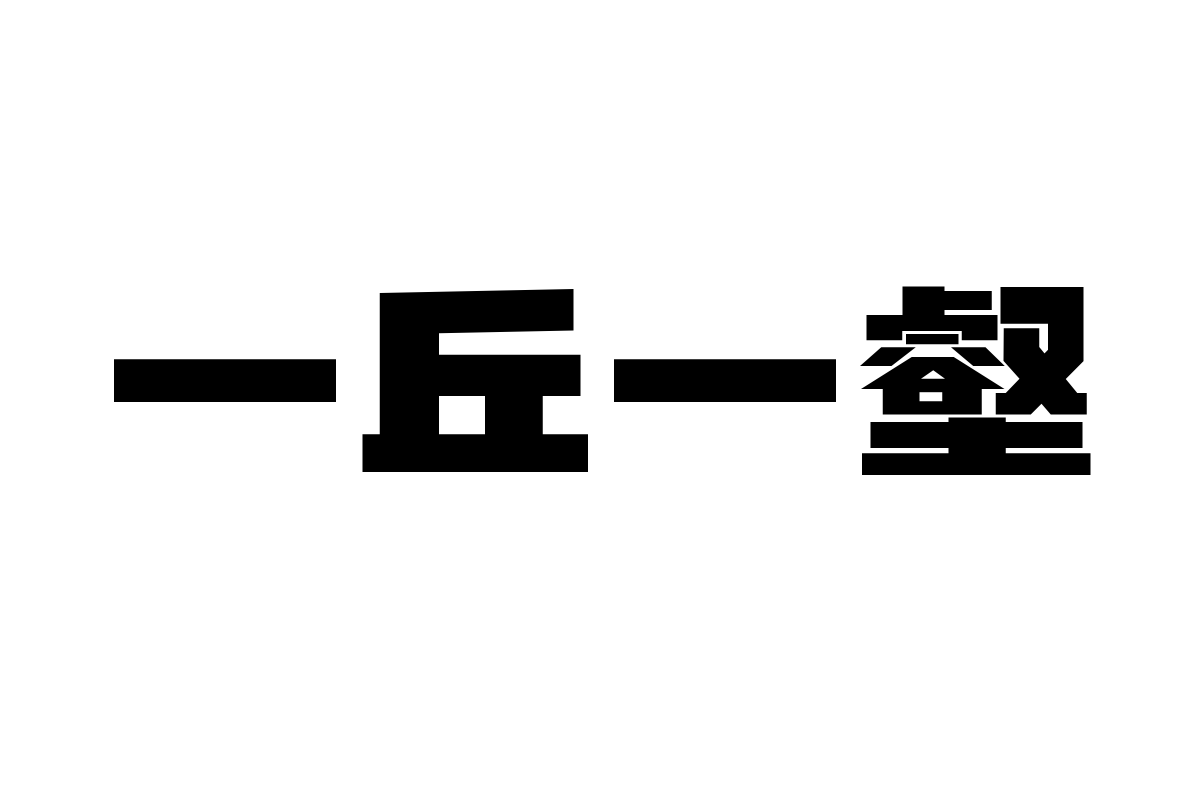
山海潮流超黑字体是一款具有独特风格的中文字体,它采用了现代的设计手法和创新的设计理念,将传统书法与现代审美相结合,打造出了一种独特的视觉体验。这款字体的特点如下:
1. 字形结构:山海潮流超黑字体的字形结构紧凑,线条流畅,给人一种动感十足的感觉。它的笔画粗细不一,既有粗犷豪放的一面,又有细腻柔和的一面,使得整体风格既大气又不失个性。
2. 字形风格:这款字体的字形风格独特,既有传统的韵味,又融入了现代的元素。它的笔画变化多样,既有直线的硬朗,又有曲线的柔美,使得整体风格既有力量感又不失美感。
3. 字间距:山海潮流超黑字体的字间距设计得恰到好处,既不拥挤也不稀疏,使得整个字体看起来既协调又美观。
4. 字重感:这款字体的字重感较强,使得整个字体看起来更加有力,更具冲击力。
5. 适用范围:山海潮流超黑字体适用于各种场景,如广告、海报、书籍、杂志等,能够为不同的设计作品增添独特的魅力。
总之,山海潮流超黑字体是一款具有独特风格的中文字体,它以现代的设计手法和创新的设计理念,打造出了一种独特的视觉体验,适合用于各种需要强调个性和创意的设计场景。